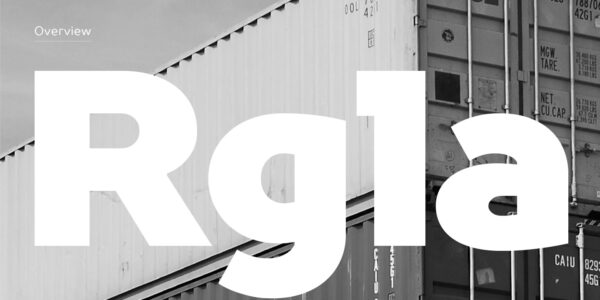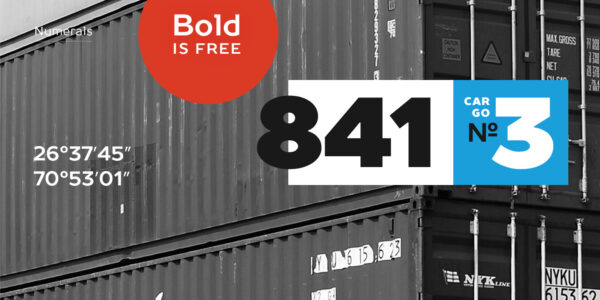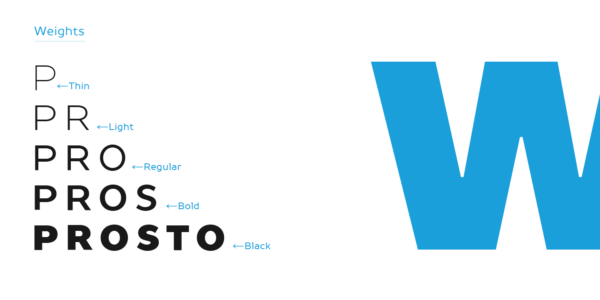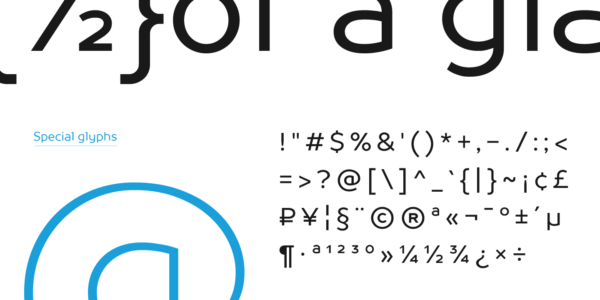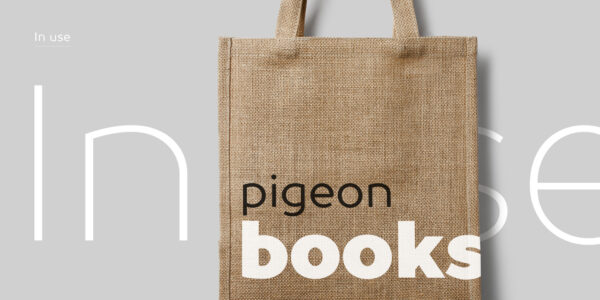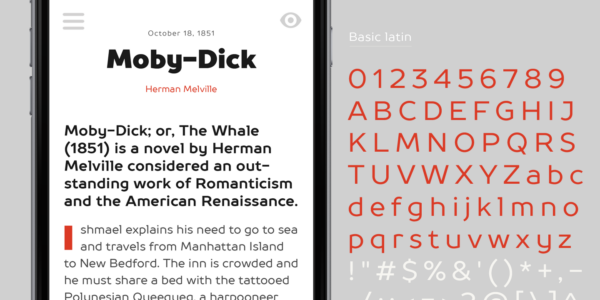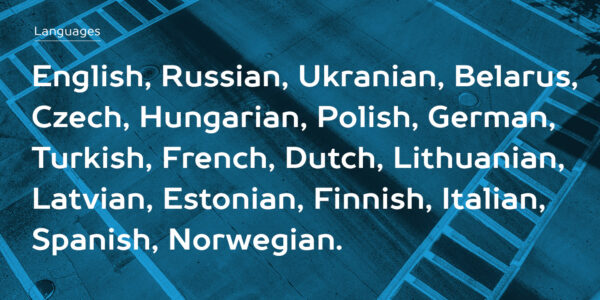
TT Prosto Sans
TT Prosto Sans — ТТ Просто Санс
Произносится «ТТ Просто Санс». «Prosto» — транслитерация слова «просто». «Sans» — сокращённое слово от английского sans serif («гротеск)». Буквы «TT» являются аббревиатурой названия компании.
TT Prosto Sans — шрифтовая гарнитура с лаконичным рисунком. Этот шрифт — простое решение для любых задач.
Гарнитура на любой жизненный случай
Prosto в названии шрифта в переводе с русского языка обозначает «Просто». Если вы имеете в своей коллекции Prosto Sans и Prosto Sans Condensed, то вы как будто обладаете универсальным инструментом, который помогает вам каждый день, когда нужно что-то «починить» или «отремонтировать». Благодаря узким пропорциям, любой текстовый массив помещается на меньшем текстовом поле, чем обычно.
Вы можете использовать гарнитуру почти для любой задачи
TT Prosto Sans — помощник в работе над проектом любой сложности
О гарнитуре TT Prosto Sans
TT Prosto Sans является шрифтовой гарнитурой на любой жизненный случай. Благодаря современным открытым гротескным формам, вы можете использовать гарнитуру почти для любой задачи. TT Prosto Sans выполнен по классической формуле: Thin, Light, Regular, Bold, Black and Italics. TT Prosto Sans — это ваш помощник в работе над проектом любой сложности.
case | Case Sensitive Forms
frac | Fractions
numr | Numerators
dnom | Denomerators